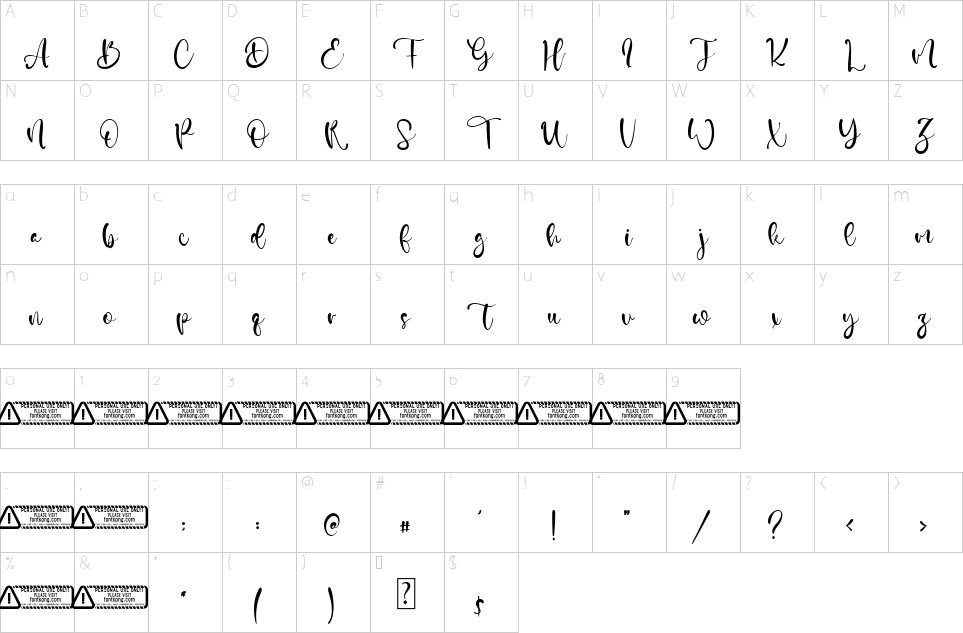
A Sally Gates font oferece um ar elegante e sofisticado para escritas de qualidade. Desenhada pelo designer anônimo da Font Kong, esta fonte gratuita para Windows e Mac foi projetada para complementar qualquer projeto de design gráfico. Com seu design cuidadosamente refinado, Sally Gates tornar se adequada para textos de grandeza, desde títulos chamativos até linhas de texto mais sutis. Com apenas 1.725 downloads, esta fonte é uma excelente opção para aqueles que buscam estilo sem comprometer o tamanho do arquivo. Perfect para estilos como o minimalista, a Sally Gates font adiciona um toque de classe a qualquer trabalho de design. Descubra agora e dê vida a seu design.